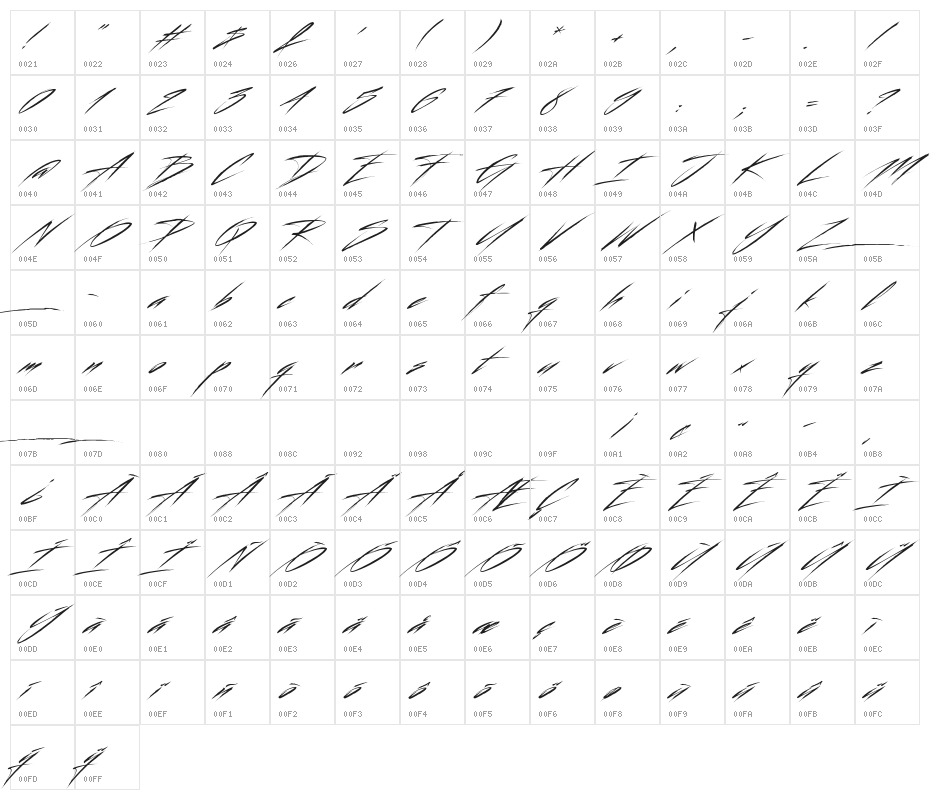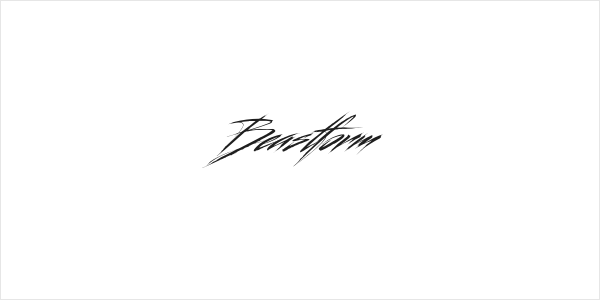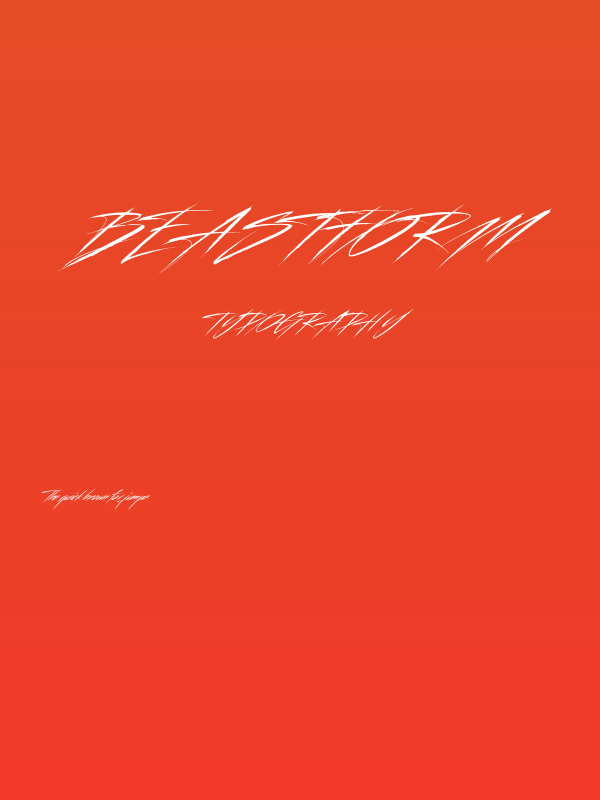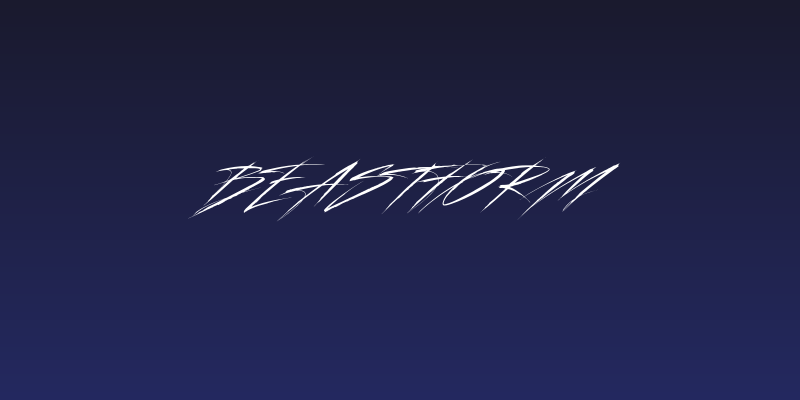
Beastform Font
✎ Calligraphic
| Stile generale | Modern, Energetic |
| Progetti proposti | Perfect for sports branding, music album covers, dynamic posters, and edgy fashion labels. |